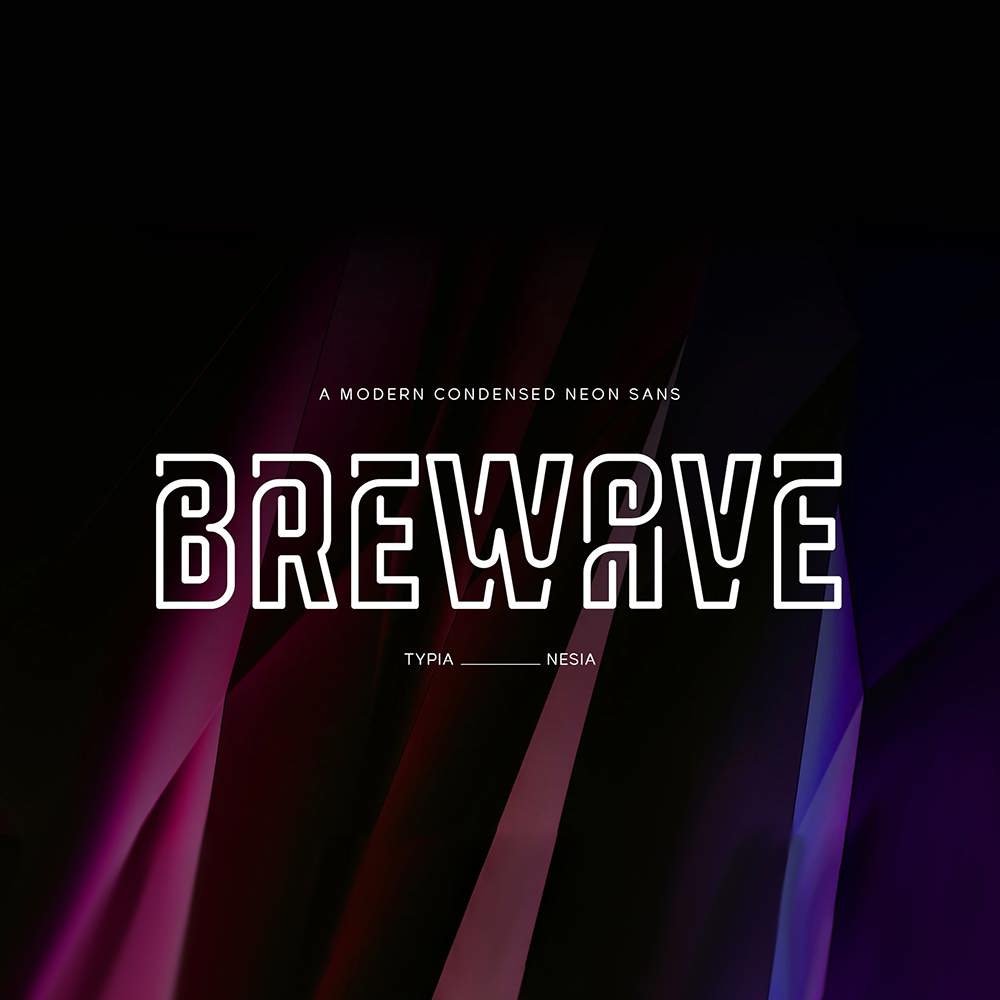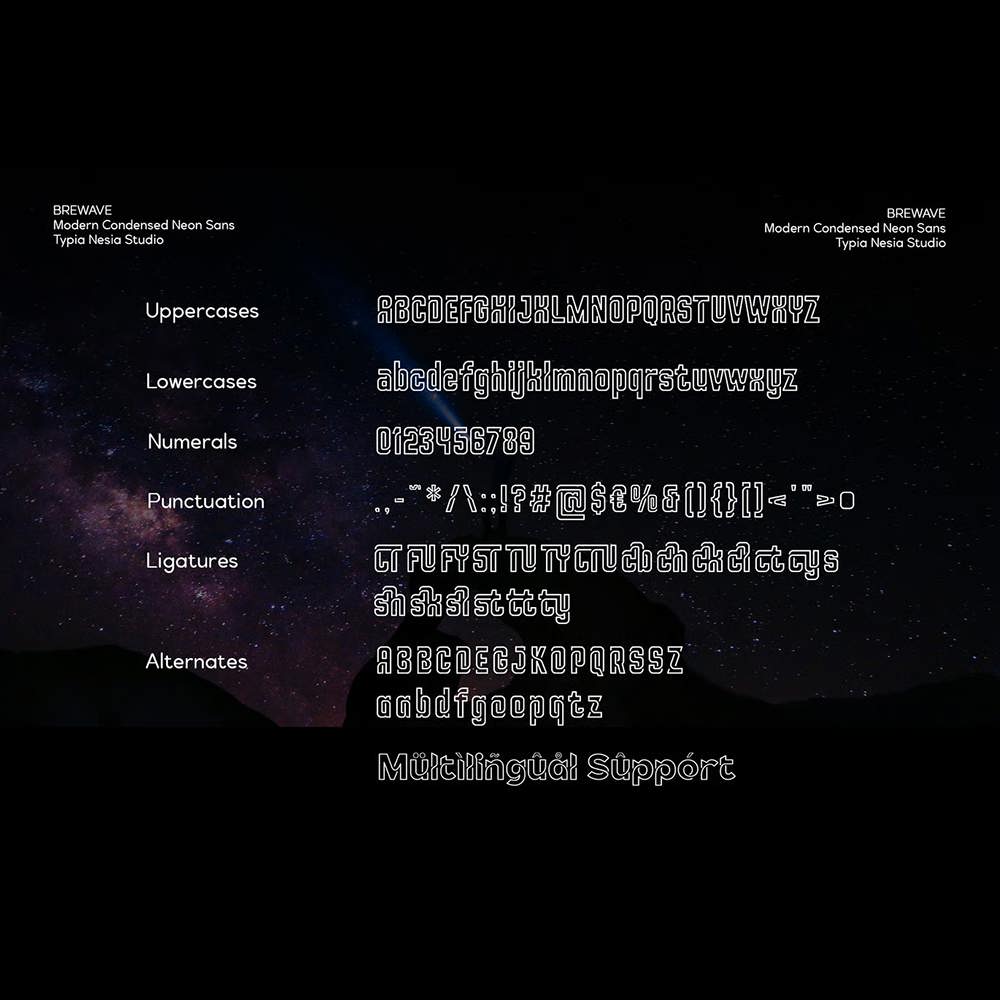
فونت پرمیوم و انگلیسی Brewave Font فونت نمایش تابلوهای نئونی کافههای قدیمی است. فونت Brewave برای پروژههایی مانند لوگو، طراحی سرمقاله، طراحی لوازم التحریر، طراحی ورزشی، طراحی رترو دهه ۱۹۸۰، طراحی بازیهای ویدیویی، پوسترهای موسیقی، طراحی وبلاگ، طراحی تبلیغات مدرن، کارتهای دعوت، نقل قولهای هنری، طراحی داخلی، عناوین کتاب/جلد، رویدادهای ویژه و… عالی است.